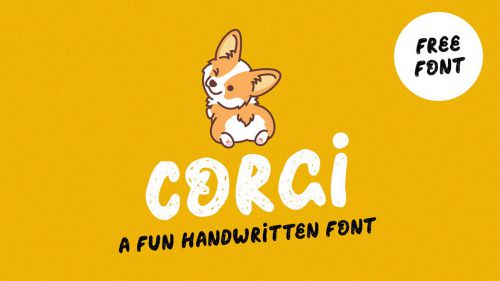
Corgi
【Corgi:趣味涂鸦风英文手写体】 Corgi是一款充满趣味的英文手写体,以独特的涂鸦风格展现手写文字的灵动魅力。作为免费商用字体,其粗重饱满的笔触与圆润设计,为创意设计注入活泼气息。 Corgi采用扁宽的字型设计,重心居中且中宫宽博,整体视觉舒展大气。字体笔画以圆润笔触为核心,粗重均匀的线条搭配圆头笔画形态,兼具力量感与亲和力。笔画间的断开处理保留了手写的随性特质,让每一个字母都如同即兴创作的涂鸦作品。 Corgi支持常规英文(拉丁)字符集,字重饱满醒目,适合用于创意标题、社交媒体配图、儿童读物等场景。作为免费商用字体,Corgi为设计师提供了兼具个性与实用性的 typography 解决方案,轻松打造活泼有趣的视觉效果。